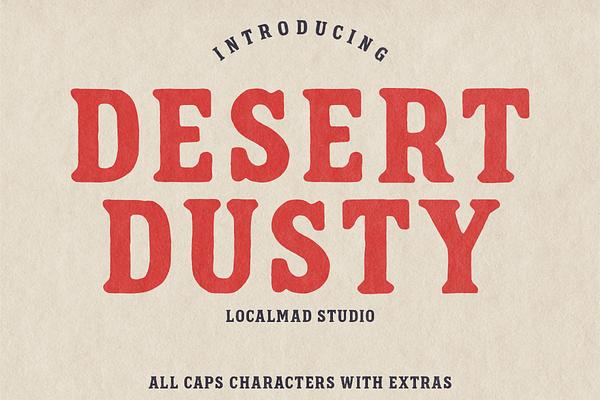
Desert Dusty 粗体英文字体
Desert Dusty - Font & Extras
这是一款复古风格的粗体英文字体,以红色大写字母呈现,背景为米色纸张质感,带有做旧效果。字体笔画厚重,边缘略显粗糙,呈现出沙漠风的粗犷与质朴感。适合用于海报、品牌标志、包装设计等需要突出视觉冲击力的场景。